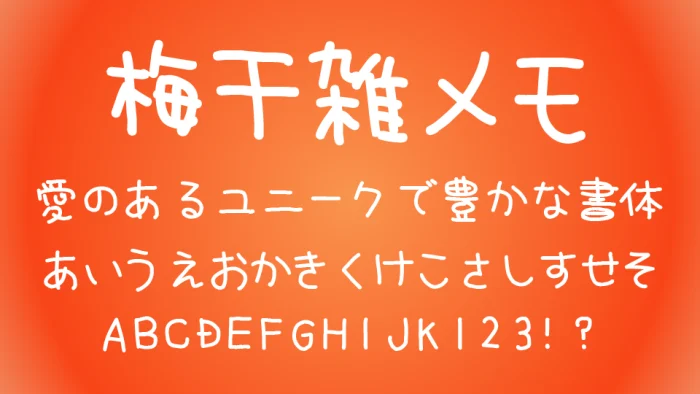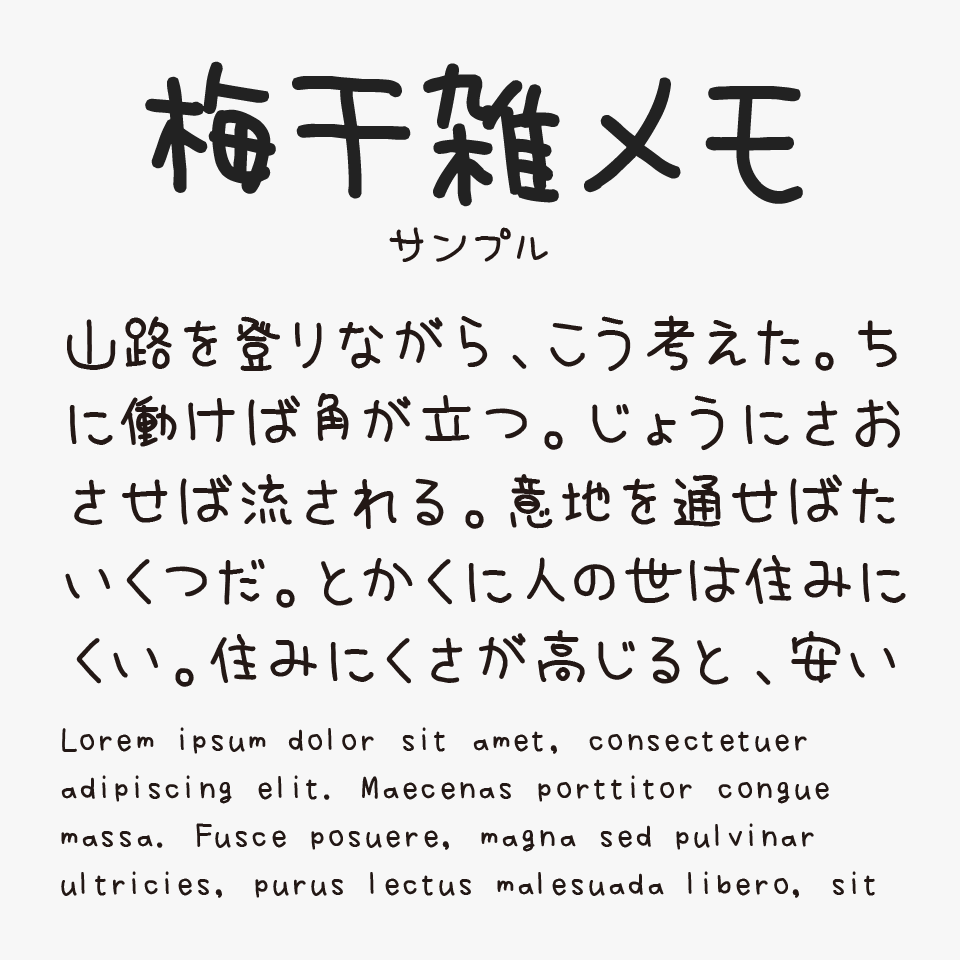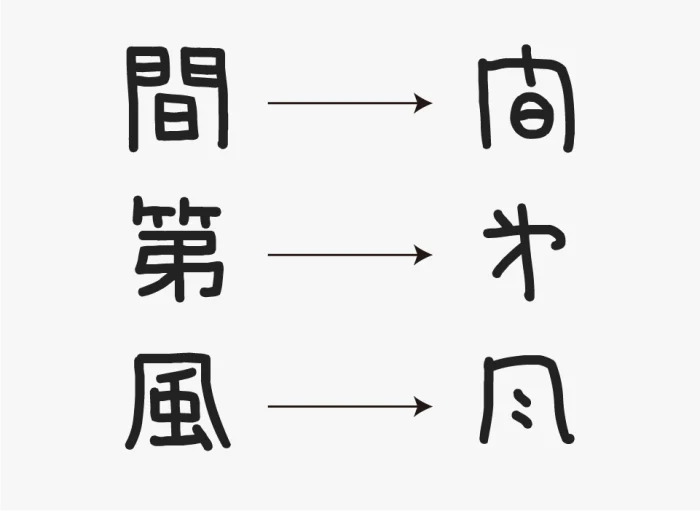
梅干雑メモ
梅干雑メモフォントは、ラフに書き留めたメモのような自然体の線が魅力的な手書きフォントです。
ほどよく力の抜けた手書き感と、少し不揃いな文字バランスが親しみやすく、気取らない空気感を生み出している可愛らしい手書きフォントです。
さらっと書いたように見えながらも、ところどころに個性的なクセがあり、素朴さの中に独特の味わいを感じられるフォントです。
一部の文字が、略字となっているのも梅干雑メモフォントの特徴です。